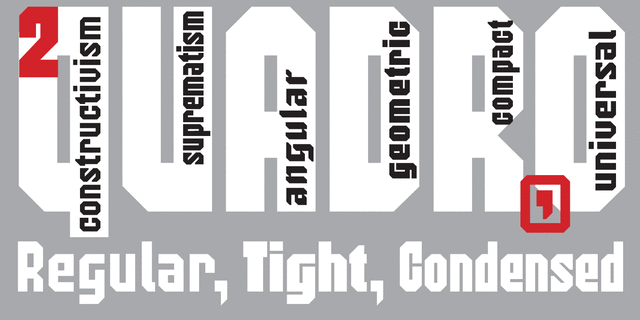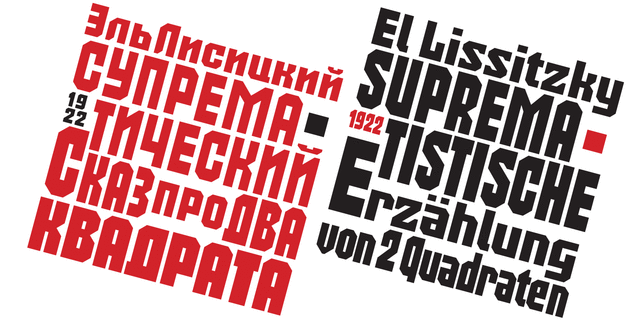
Эта гарнитура обобщает и развивает традицию плотных квадратизованных подрезанных под 45° гротесков, известных ещё с середины 19 века, активно используемых в разные времена (нп. в 1920-е, 1970-е), и не теряющих актуальности сейчас, благодаря грубоватой выразительности, монументальности и возможности максимально заполнять плоскость, не теряя читабельности. Хорошо подходит для вписывания в буквы фотографий и создания геометрических конструктивистских композиций. Шрифт разработал Виктор Харик в 2014 году.
Качества и характер:
тяжелый ,
авторитетный ,
внушительный ,
серьезный ,
убедительный ,
твердый ,
железный ,
надежный ,
мужественный ,
уверенный ,
стальной ,
грубый ,
ностальгический ,
тоталитарный ,
громкий ,
ровный ,
сильный ,
кондовый ,
устойчивый ,
политический ,
коммунистический ,
революционный ,
смелый ,
пролетарский ,
тесный ,
сжатый ,
плотный ,
важный ,
точный ,
прямоугольный ,
индустриальный ,
техногенный ,
военный ,
армейский ,
красный ,
монументальный ,
солдатский ,
урбанистический ,
рабочий ,
мотивирующий ,
амбициозный ,
суровый ,
блатной ,
заметный ,
яркий ,
активный ,
броский ,
крутой ,
железнодорожный ,
городской ,
инженерный ,
статичный ,
автоматический ,
чертежный ,
брутальный ,
кричащий ,
мощный ,
электронный ,
квадратный ,
холодный ,
резкий ,
четкий ,
машинный ,
космический ,
промышленный ,
ломаный ,
угловатый ,
граненый ,
спортивный ,
игровой ,
урбанистичный ,
черный ,
высокий
Особенности семейства 2Quadro